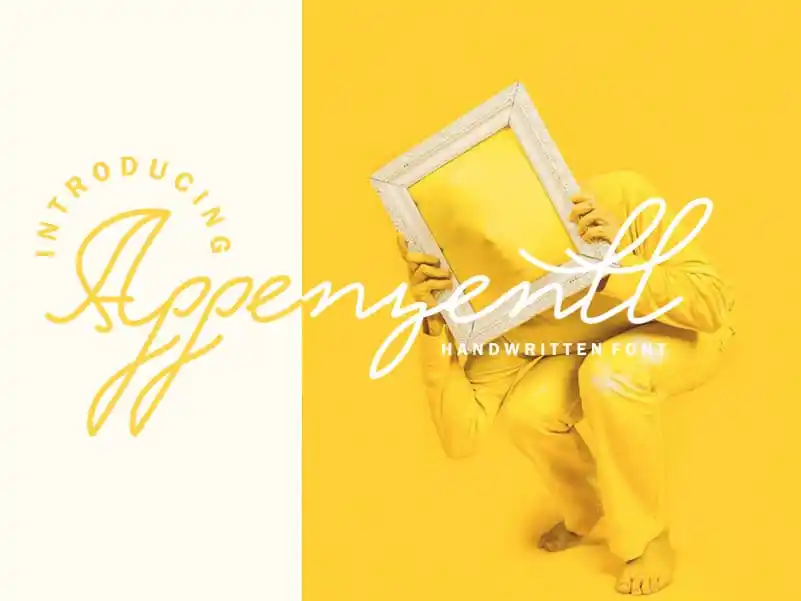
Appenzell Free Script Font – Fonte Grátis
Appenzell Free Script Font
Appenzell Free Script Font é uma opção irresistível para designers que buscam personalidade e criatividade em suas criações digitais. Desenvolvida por Khaiuns, esta fonte escrita a mão captura o charme único de um estilo livre e descontraído. Perfeita para criar designs inovadores e destacados, seja ela usada em logotipos, gráficos de marketing ou qualquer outro projeto visual. Este recurso é especialmente útil para quem deseja dar vida à sua criação com uma escrita autêntica e única, adicionando um toque pessoal que destaca a qualidade das suas produções.
Designer: khaiuns